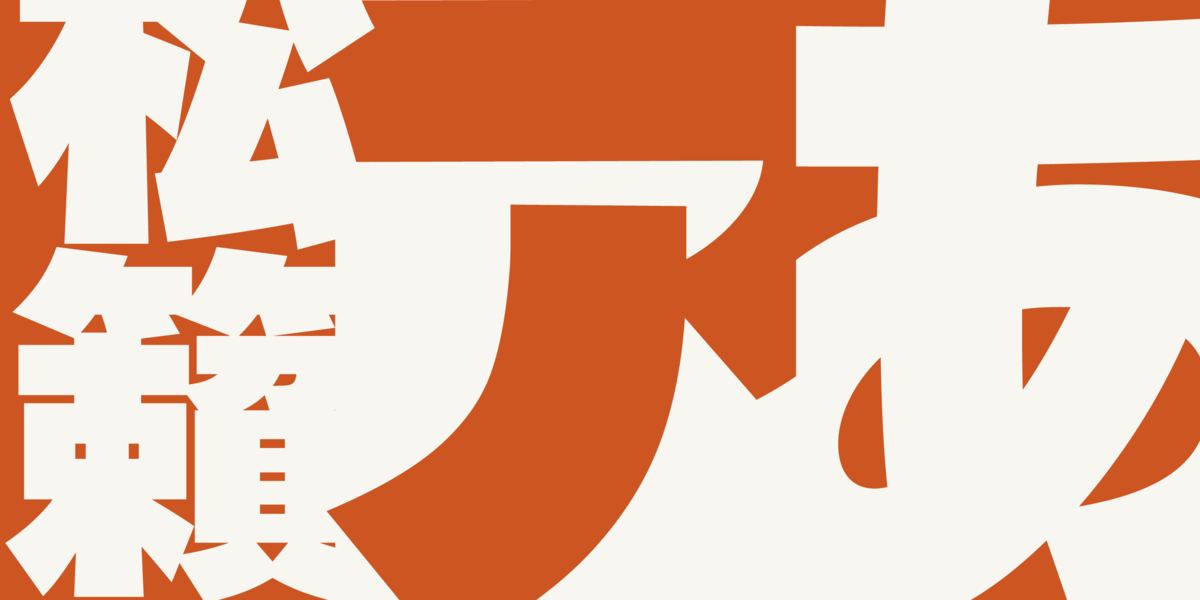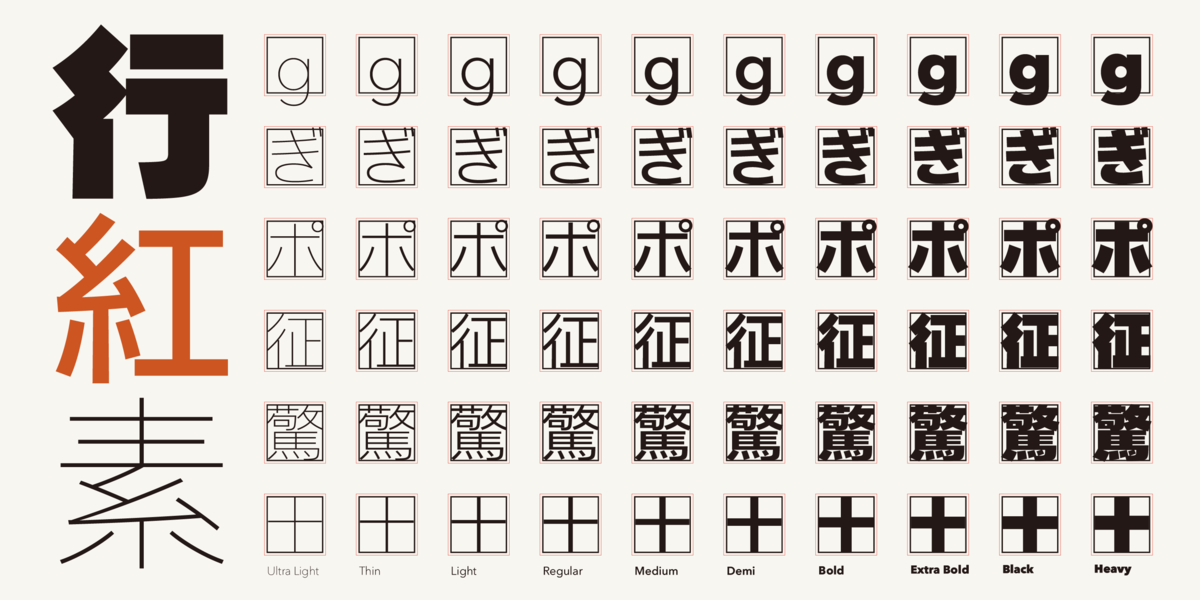
Monotype日本語書体「Shorai Sans」2022年度グッドデザイン賞を受賞
Monotype Imaging Inc.の日本法人であるMonotype株式会社は、日本語書体「Shorai Sans」が2022年度グッドデザイン賞を受賞しましたことを発表した。
Shorai Sansの概要
AvenirR Next[*1]の造形的要素を持つ日本語書体「Shorai Sans™️」は、たづがねR角ゴシック、たづがね角ゴシック Infoに続き、約3年の開発期間を経て完成された。
幾何学的でシンプルな美しさと読みやすさが特徴の書体となる。
付属欧文には和文にあわせてサイズや位置を調整したAvenir Nextを採用し、和欧混植に最適化。
たづがね角ゴシック同様、和文と欧文を別々の書体から選ぶ必要がなく、Shorai Sans単体で美しく読みやすいテキストを組むことができる。
審査員によるShorai Sansの評価コメント
「和文と欧文のバランスに優れた、非常に汎用性の高いフォントである。欧文フォントのAvenir Nextとマッチするよう最適化されているため、和文と欧文の混在するグローバルな情報発信で活躍するだろう。バリアブルフォントの幾何学性と、繊細な手書き感の組み合わせも絶妙である。極太から極細まで10ウェイトと、幅広いファミリー構成でありながらも統一感を失わないデザインが素晴らしく、太いウェイトでも高い視認性が保たれている点も高い評価となった。」
Shorai Sansの特徴
文字の線をできるだけ整理し、骨格を極限まで単純化。
線を均一に保つことで、すっきりと読みやすい明快な形を目指している。
シンプルで見やすい文字は、印刷物のほか、スマートフォンやタブレット端末などのデジタルデバイス、建物や標識のサインまで、幅広いニーズに対応している。
文字の太さは超極太から極細までの10種類。
最も太いウェイトの Heavy では、複雑な輪郭線を整理し、Monotype初の超極太の日本語書体を実現した。
通常の単体ウェイトに加えて、文字の太さや幅などをユーザー側で自由に調整できるバリアブルフォントを採用し、ウェイト間の太さも調整できる。
ウェブサイトや映像などのスクリーン上で動きのある文字表現も可能となる。
デザイン開発はMonotypeの小林章氏、土井遼太氏、そして書体デザインの第一人者である中村征宏氏によって行われた。
基本となる漢字400字ができる頃、Monotypeの日本、香港、ドイツオフィスの書体デザイナーとエンジニア、そして中村氏が香港に集まり、1週間ほど一緒に書体制作。
日本語書体の制作では、書体デザインを終えてからエンジニアにバトンタッチするのではなく、両方を同時に進めた方が効率的であると過去の経験から学んだため。
将来の字種拡張も考慮し、最初から多国籍メンバーで開発を進め、世代や文化を超えたコラボレーションとなった。
人間らしい自然な筆の動きをイメージしたたづがね角ゴシックに対し、Shorai Sansは「何も足さない『素』のかたち」をテーマに、読みやすくクリーンで理知的な印象の書体に仕上げられた。
書体名の「Shorai(ショウライ)」は、松の枝を吹き抜ける風やその音の意味である「松籟」に由来している。茶道では茶釜の湯がたぎる音を意味し、日本的で優雅な響きのある名前で、誰でも発音しやすく、世界中の方々にお使いいただける日本語書体となる。
[*1] アドリアン・フルティガー氏と Monotype クリエイティブタイプディレクターの小林章氏が共同制作した書体ファミリー。オリジナルの Avenir を改刻、ウェイト数を大幅に増やし、OpenType フォントとして 2004年に発売。
Shorai Sans(ショウライ・サンズ)